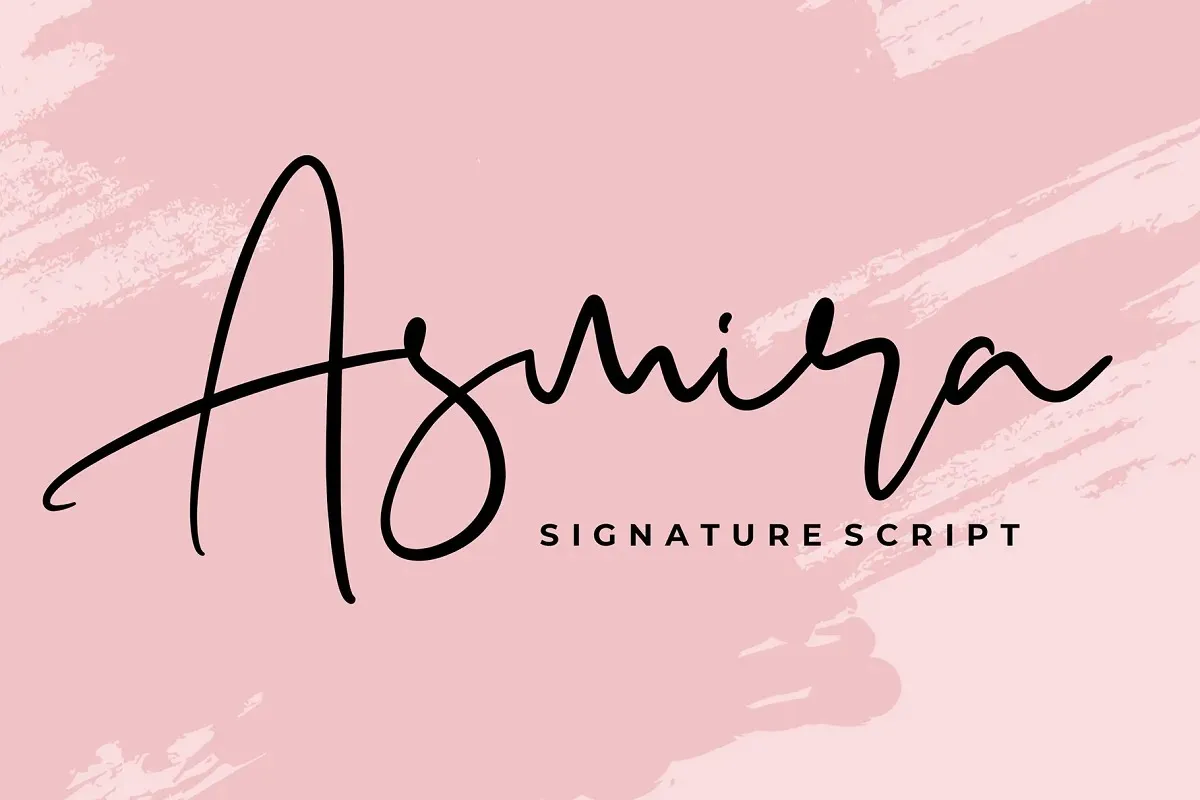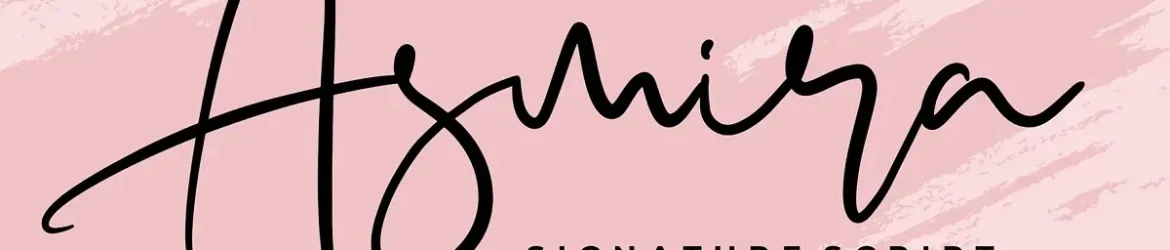
A Asmira Font é uma nova fonte à mão livre com contraste de traço alto, inclinada e caracteres divertidos com pequenas ligaturas, criada pelo designer Formatika Studio. Esta fonte traz um toque fresco e autêntico da arte do desenho a lápis, perfeita para criar trabalhos criativos em logotipos, redes sociais, títulos de filmes, livros, até mesmo textos longos ou secundários no estilo serif. Seja seu texto principal ou fonte secundária, Asmira é uma excelente escolha para estilos sans-serif e serif. Esta font está perfeitamente equipada para se tornar o ponto alto de qualquer projeto – seja em sua identidade visual ou ao dar vida à sua próxima peça gráfica. Com Asmira Font, você terá a opção de criar designs incrivelmente detalhados e memoráveis. Aqui, o design não é apenas uma questão de estilo; é um processo que permite explorar as fronteiras do seu trabalho criativo, tornando-o único e impactante.